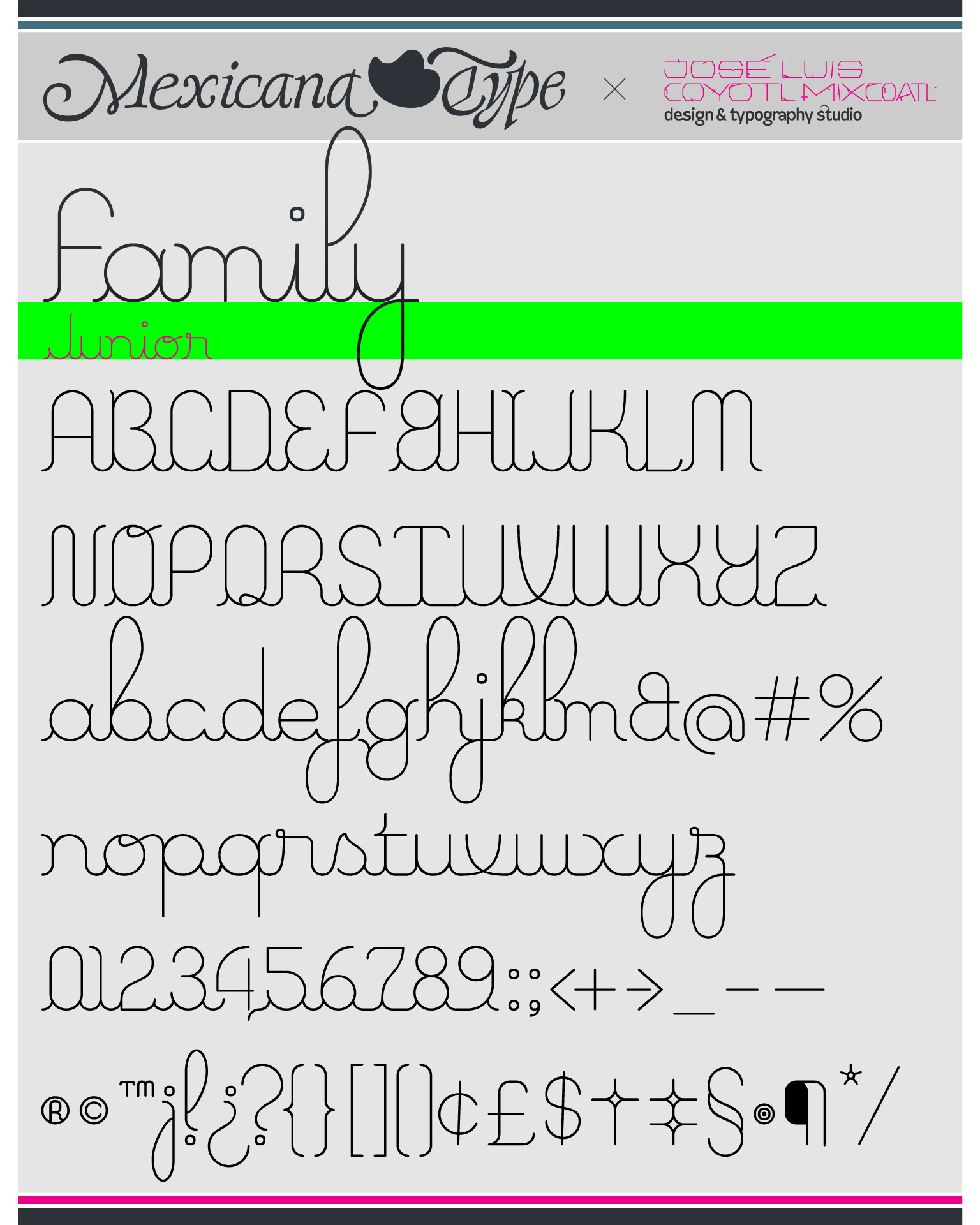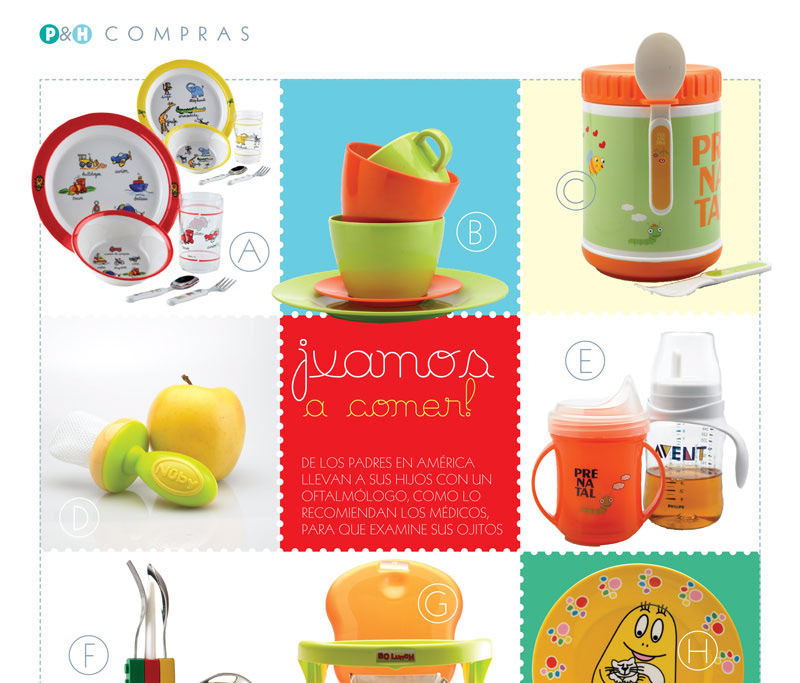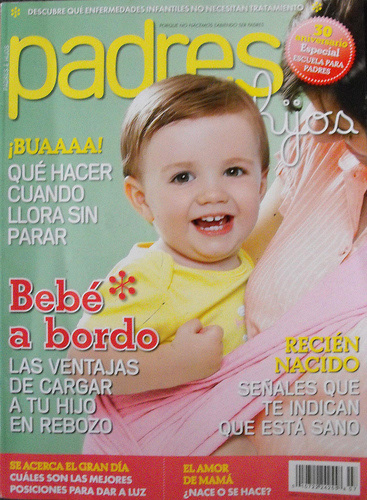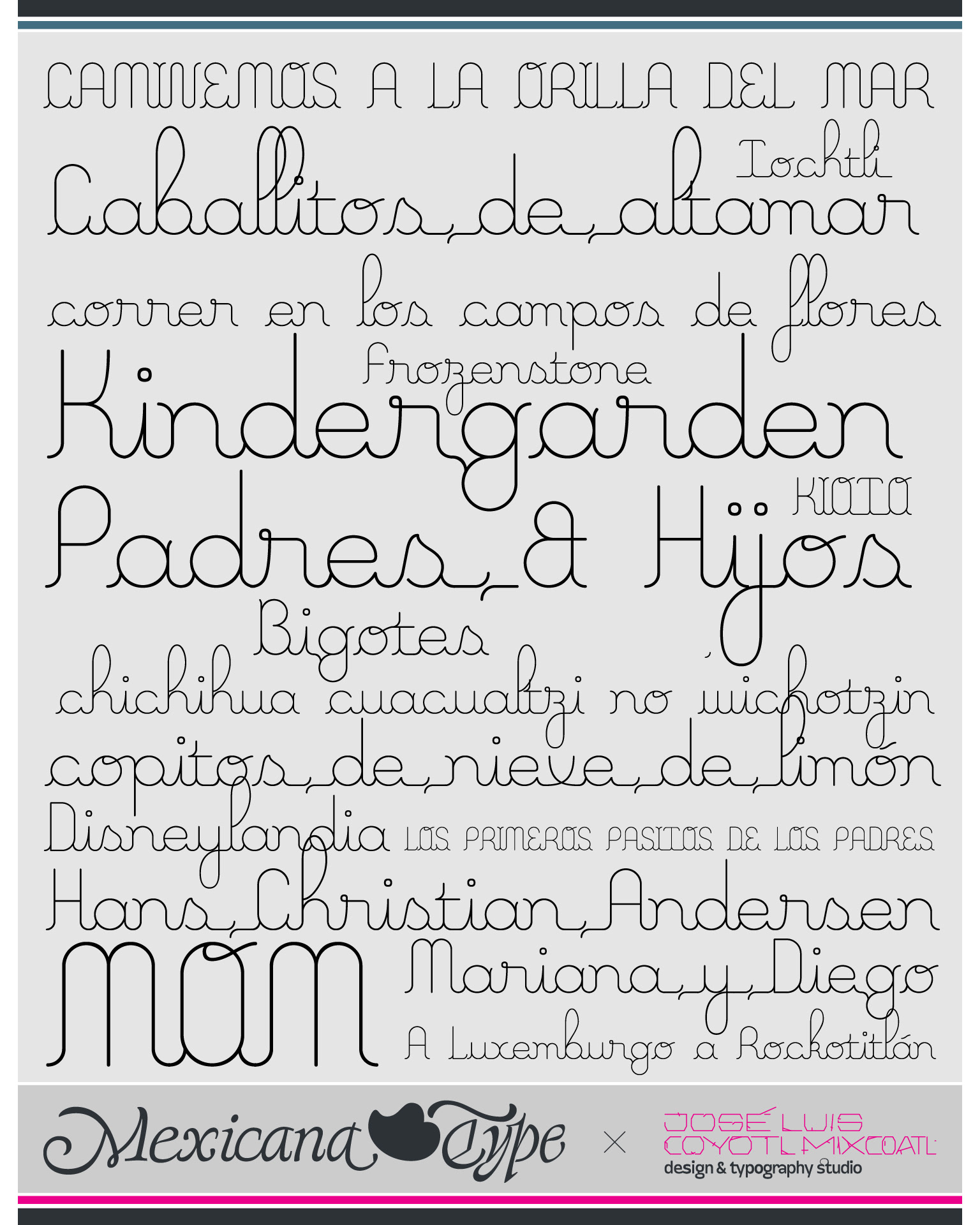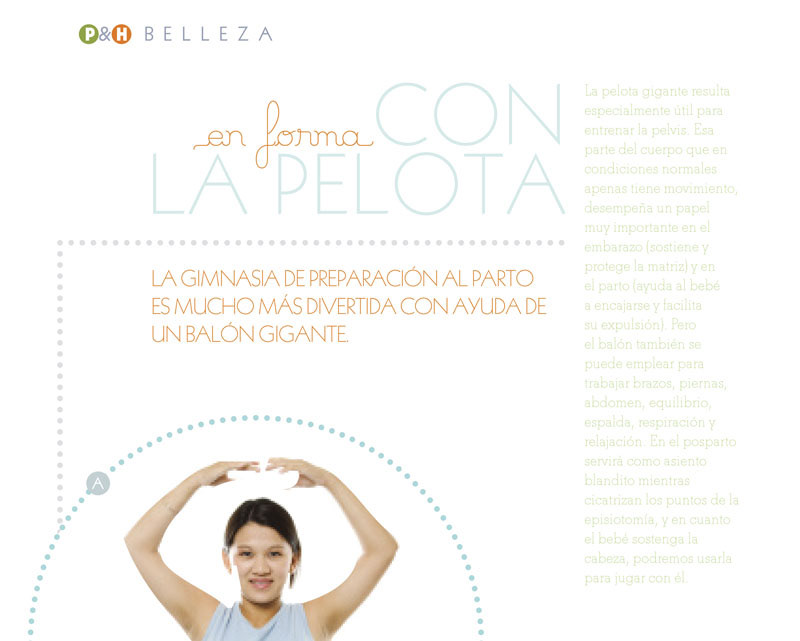
Padres & Hijos
Custom Type para revista
Tipografía personalizada diseñada para la revista mexicana Padres & Hijos de Editorial Televisa.
Diseñada para titulares y títulos, la tipografía Family se creó originalmente con un solo grosor: Junior. Tras el proyecto, se añadieron dos variaciones más: Senior y Mother.
El proyecto se desarrolló para el estudio de diseño La Fe Ciega en la Ciudad de México. También formé parte del equipo de diseño que rediseñó la revista, lo que me permitió comprender las necesidades de la tipografía y ampliar las posibilidades que buscábamos como estudio de diseño.